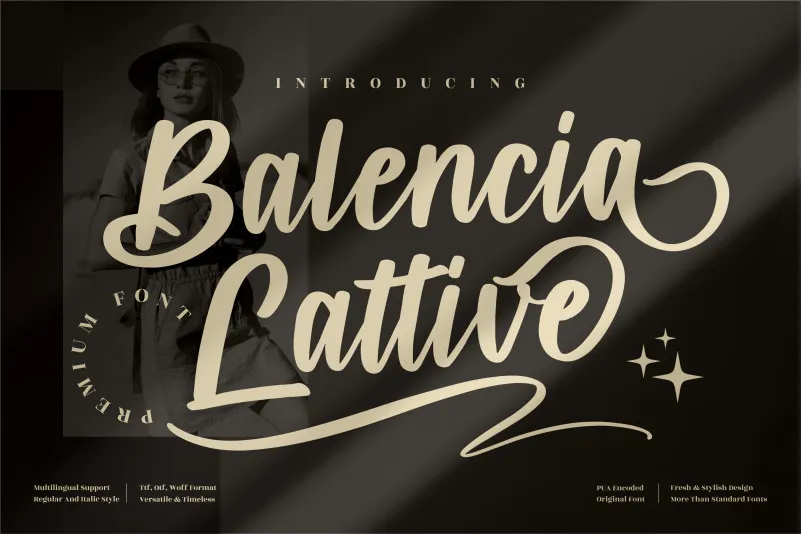
A Balencia Lattive Font é uma elegante tipografia que se destaca em qualquer projeto onde você procura um toque singular e sofisticado. Perfeita para criações como logomarcas, designs de marca, embalagens de produtos, vasos de café ou mesmo etiquetas de produto, essa fonte premium traz a resolução perfeita para itens de luxo. Seja em uma t-shirt personalizada, um envelope de visita, até um livro com capa dura, sua versatilidade e qualidade garantem que estejam impecáveis. Compreender o valor da exuberância e do cuidado, esta fonte é a escolha perfeita para celebrar os momentos especiais ou simplesmente adicionar um toque de sofisticação aos seus projetos. Seja você uma agência de design ou um pequeno empreendedor que busca dar um diferencial a suas criações, a Balencia Lattive Font certamente atenderá às expectativas do seu trabalho.